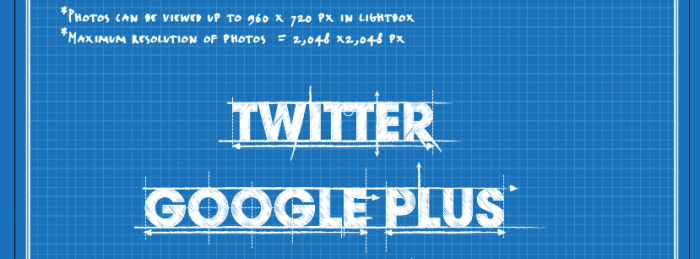
Handgezeichnete Schrift mit guter Lesbarkeit
hab mich neu hier angemeldet und auch direkt eine Frage an alle. Bin grad dabei eine Infografik zu gestalten und zwar im Hand drawn stil. Natürlich brauch ich jetzt noch die passende Schrift. Hab es mal mit der Erikrighthand ( https://www.myfonts.com/fonts/fontfont/ff-erikrighthand/ ) versucht. Die Schrift gefällt mir auch grundsätzlich sehr gut und passt auch gut ins Design. Problem ist natürlich das sie nicht wirklich gut lesbar wenn man zu klein macht.
Mein Frage wäre also jetzt: Kennt jmd eine vergleichbar Schrift die besser für Texte geeignet ist???
Comic Sans.
Spaß beiseite, schreibst Du mit der Hand in 12pt oder kleiner? Handschriftliches braucht seinen Platz. Von welchen Größen reden wir? So ab 16pt werden viele Script-Fonts lesbar. Segoe Script steht da so ein bißchen raus. Aber auch Reklame Script, Suomi Script, Rollerscript, ...
Am ehesten bekommst Du auf die schnelle eine Übersicht, wenn bei Myfonts.com nach Script suchst und die Anzeigegröße runterregelst. Dann kannst Du selbst entscheiden, wann etwas noch lesbar ist.
schonmal danke für die schnelle Antwort. Hab jetzt mal einen Ausschnitt der Arbeit hochgeladen. Ich persönlich finde das man es noch gut lesen kann, aber wie so oft geht es nicht um mein persönliches Empfinden und der Kunde ist ja König ;)
Es geht um die Sätze mit dem * dran. In anderen Teilen der Grafik gibt es auch noch ein wenig längere Sätze, aber in der Regel ist es nur ein Satz